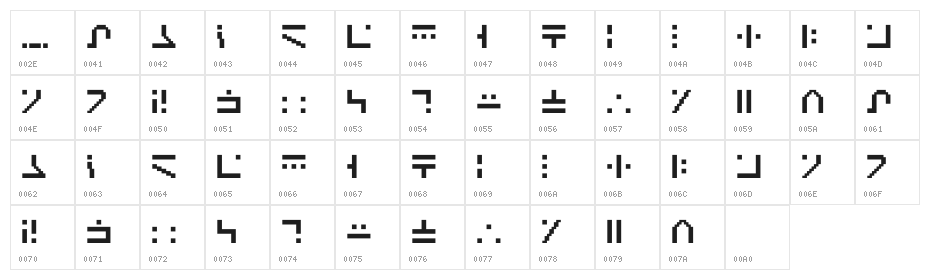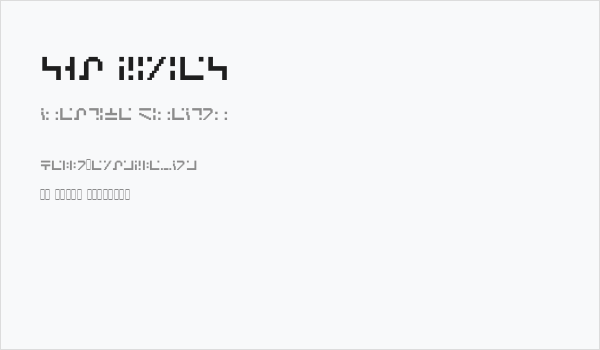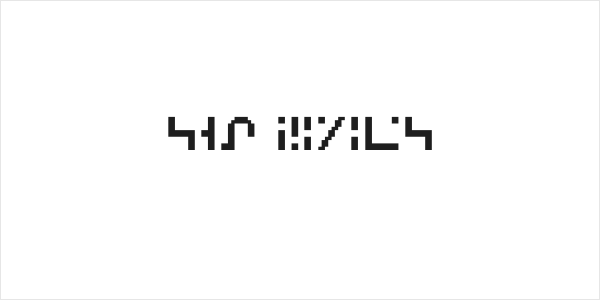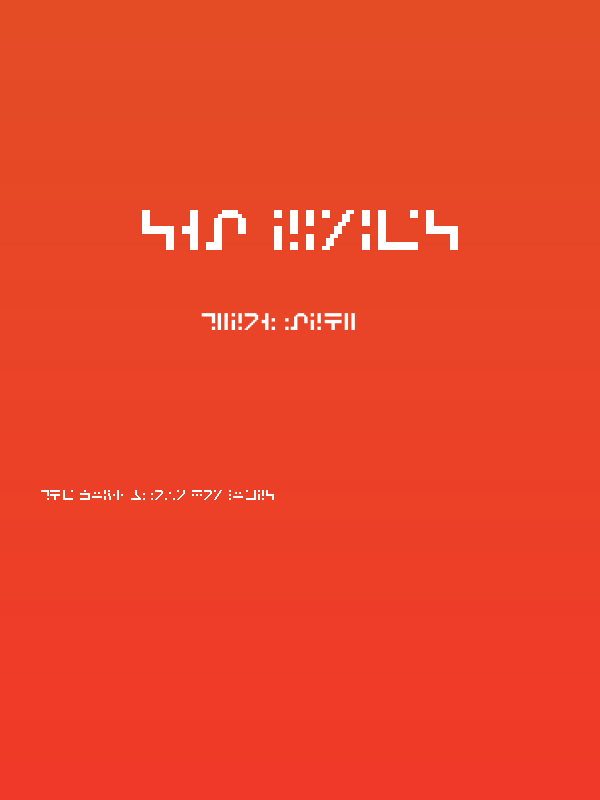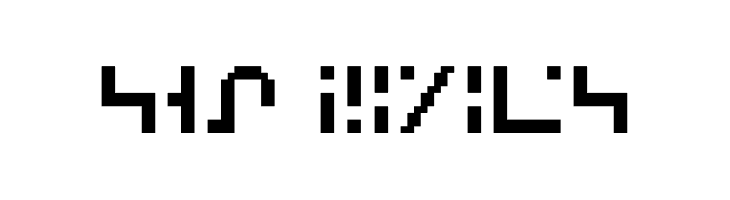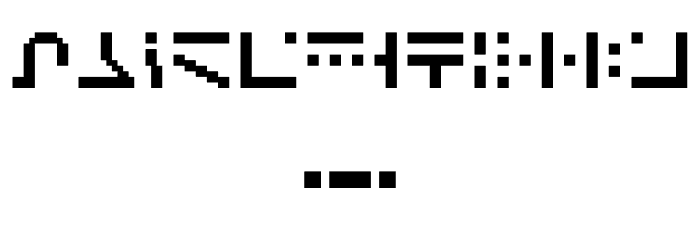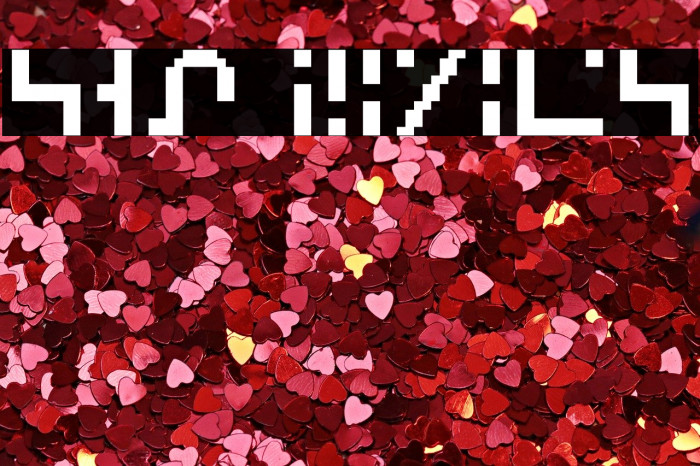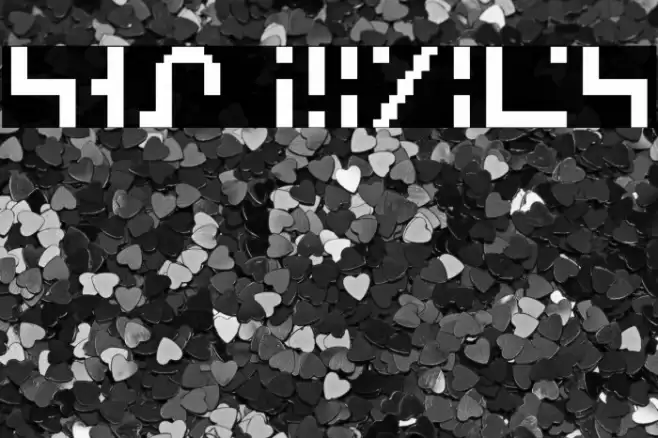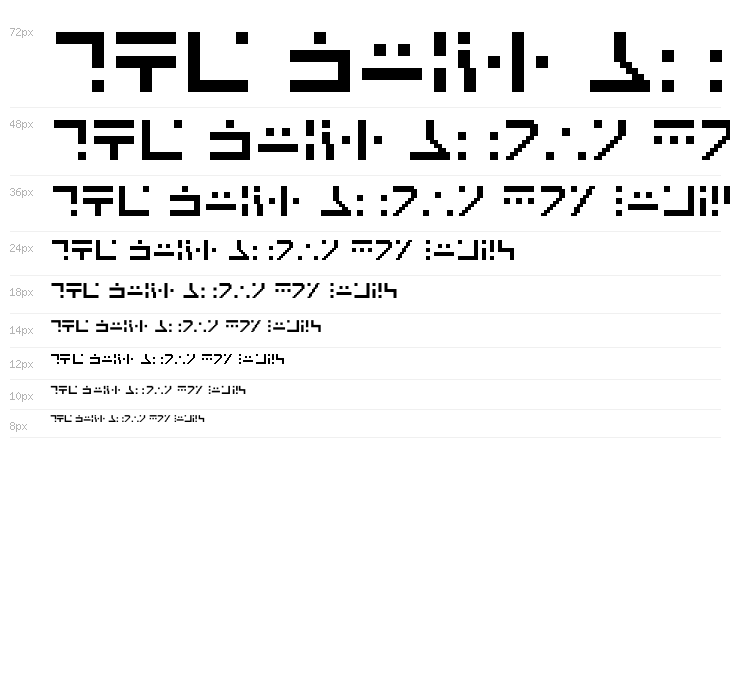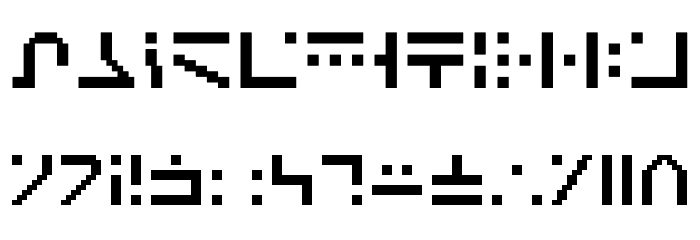
SGA Pixies Font
| Stile generale | Retro, Digital |
| Caso d'uso | Logos, Digital Art, Video Game Design |
| Progetti proposti | Ideal for retro-themed video games, digital art projects, or any design that aims to evoke nostalgia for early computing and gaming eras. |